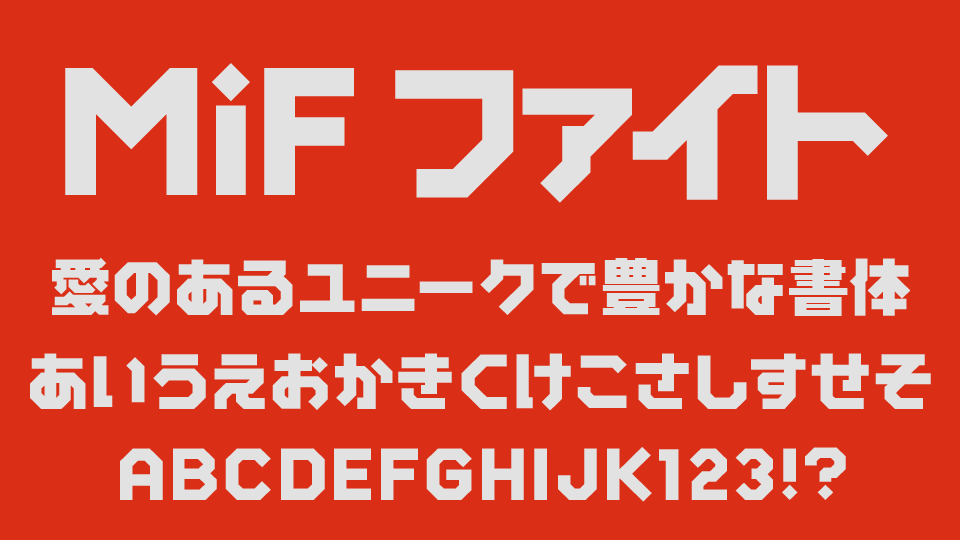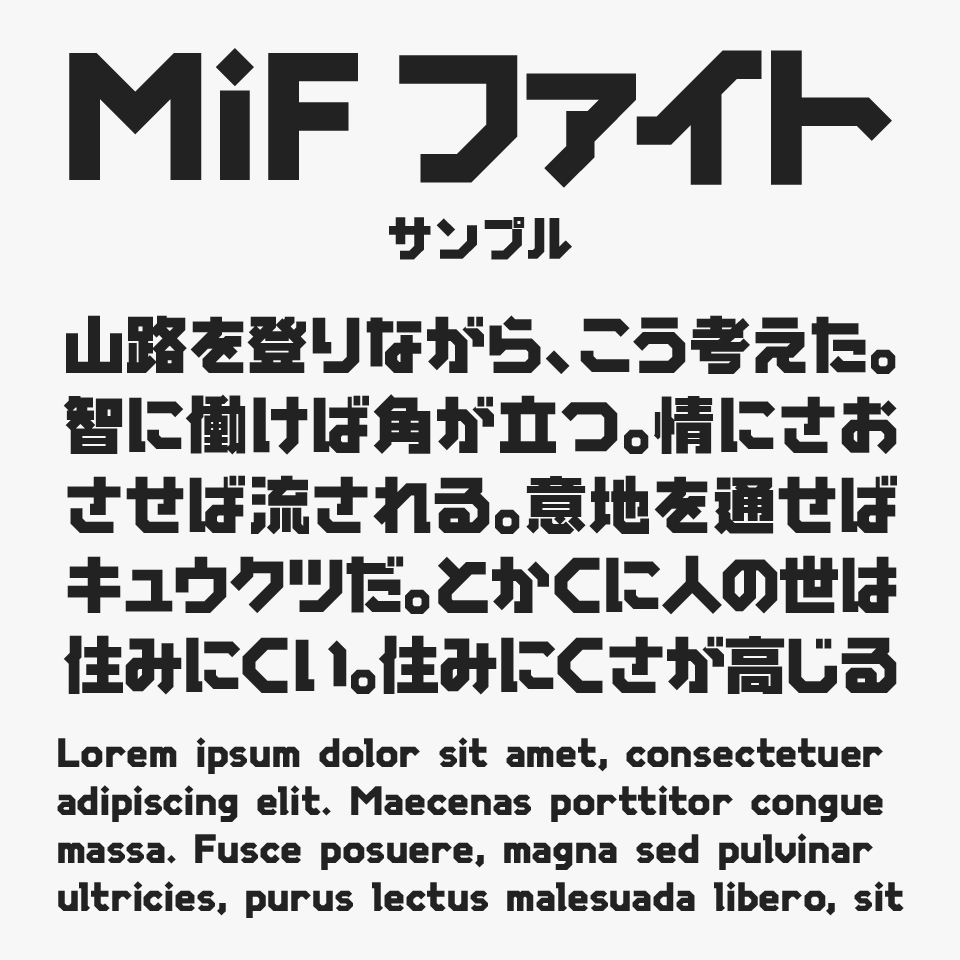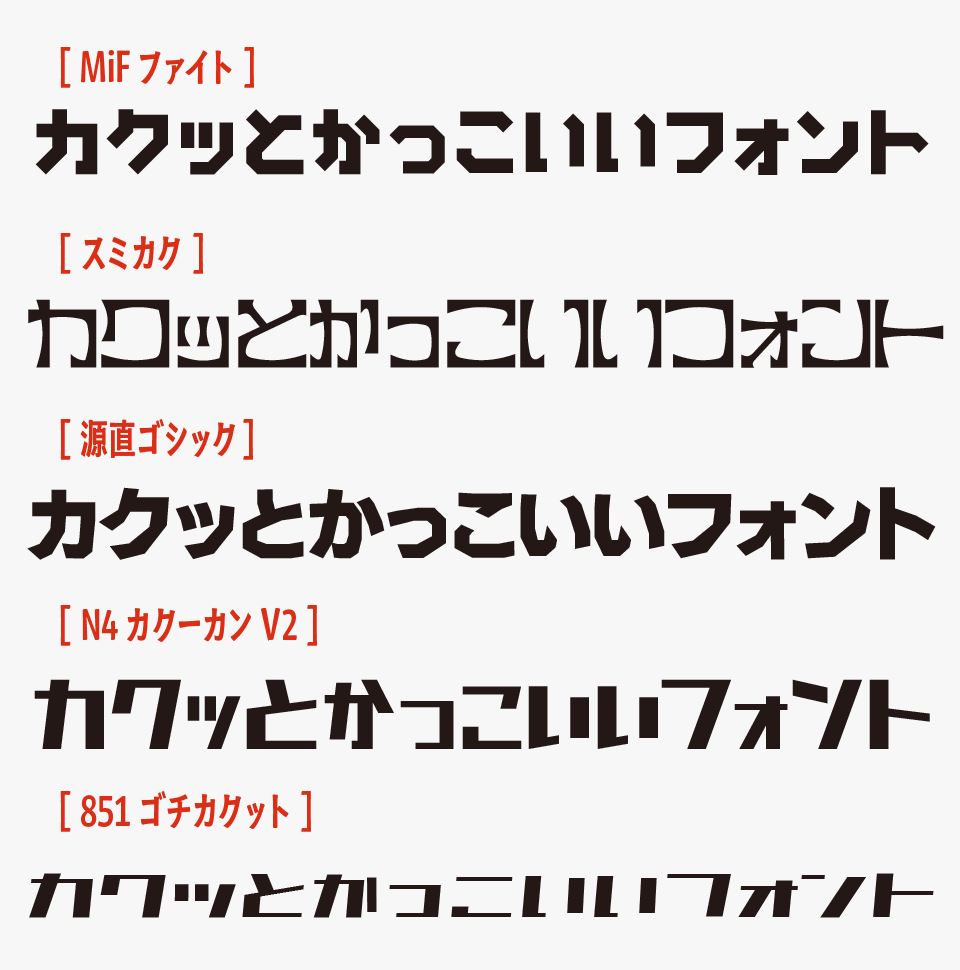
MiFファイト
MiFファイトフォントは、カクカクとした直線を基調にしたシャープな構造と、無骨で力強い印象をあわせ持つデザインが特徴のデザインフォントです。
機械的で近未来感のあるフォルムが印象的で、太めのウェイトによる高い視認性と存在感を感じられるフォントです。どこかスポーツ感やテクノロジーを連想させる、エネルギッシュでスピード感のあるフォントです。
力強さやインパクトを求める場面と相性がよく、YouTubeサムネイルやゲーム関連デザイン、イベントバナー、スポーツ系のビジュアル制作などにぴったりなフォントです。近未来やSFテイストの世界観とも馴染みやすく、目を引くタイトル表現に活躍するフォントです。
MiFファイトフォントを、ほかのカクカクとしたかっこいいデザインフォントと比較してみると、エッジのあるシャープな直線構成と近未来感のある力強さが特に際立っているフォントです。
比較フォントは、「スミカク」「源直ゴシック」「カクーカンV2」「ゴチカクット」を使用していますが、どれもカクッとしたカッコいいフォルムなフォントなので、ぜひあわせてチェックしてみてください。